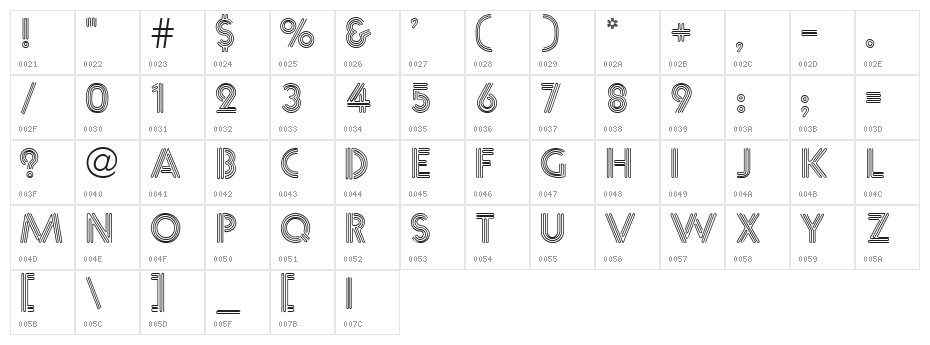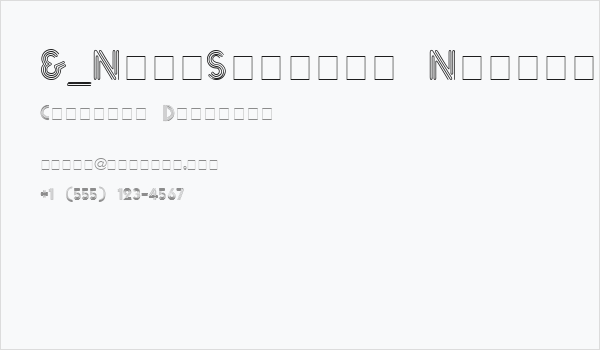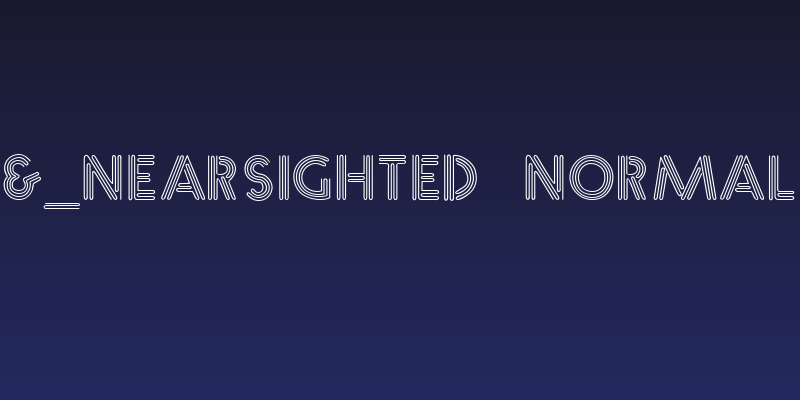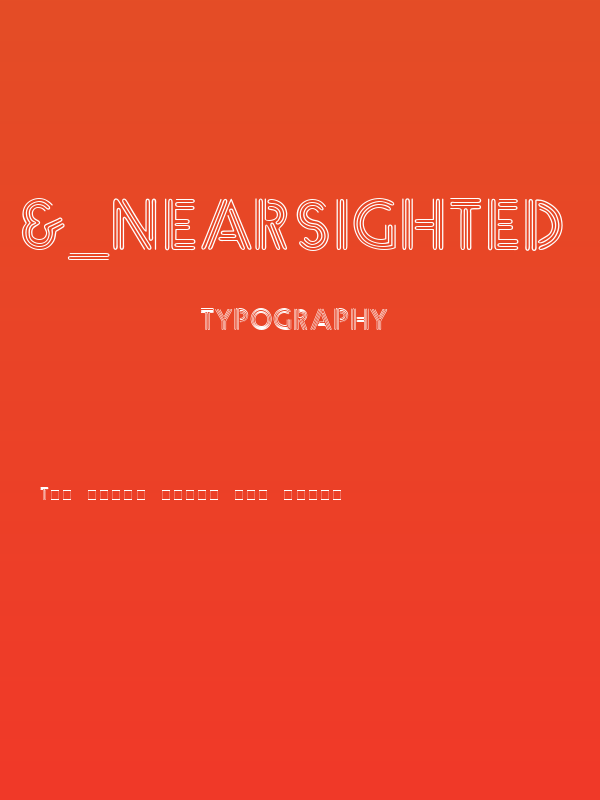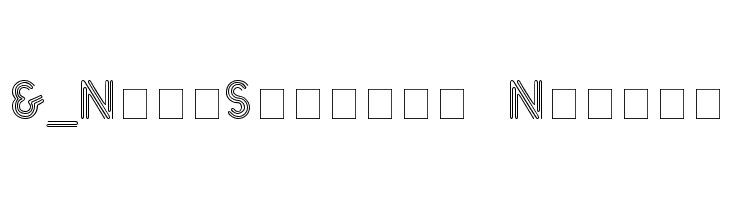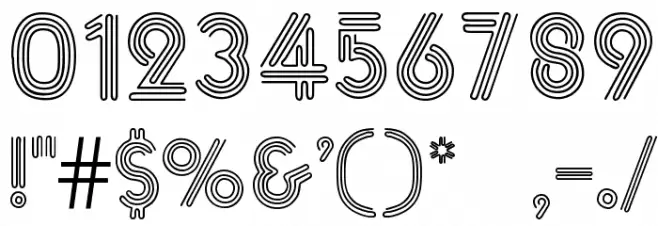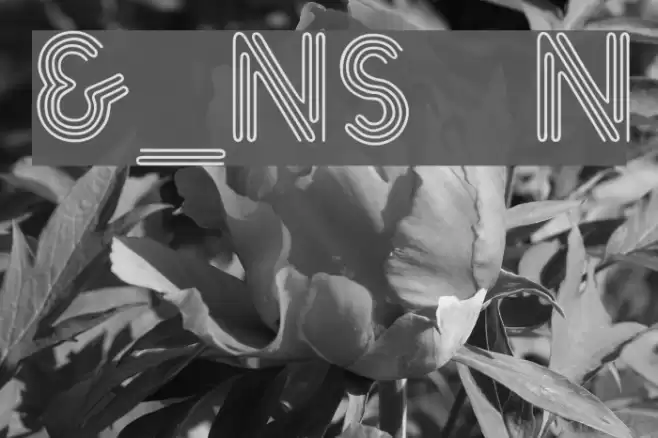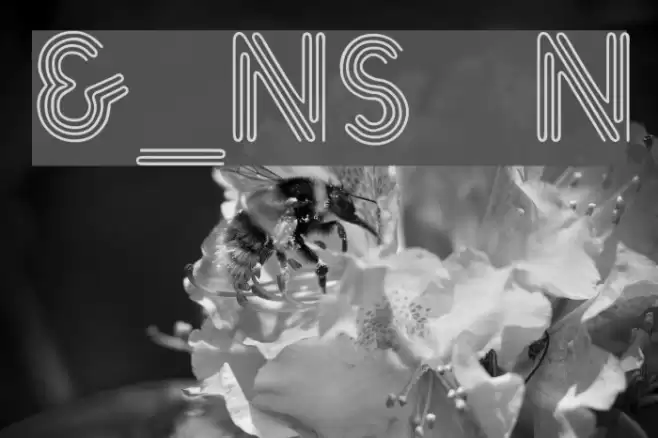
&_NearSighted Normal Font
| Gesamtstil | Modern, Decorative |
| Vorgeschlagene Projekte | Ideal for branding, posters, album covers, and any project needing a bold, artistic touch. |